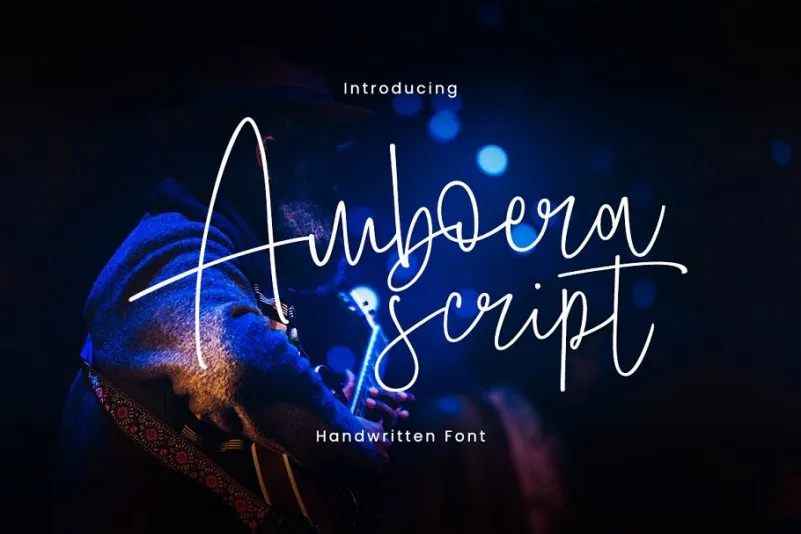
Amboera Handwritten Font – Download Grátis
Descubra a elegância e a naturalidade da Amboera Handwritten Font, uma nova opção para sua paleta de tipos de escrita. Esta tipografia é criada pensando no uso pessoal ou na marca, com um design meticuloso que transmite uma atmosfera amigável e descontraída. Introduzida pela Daikian, a Amboera Handwritten é perfeitamente concebida para ser usada em aplicações formais como cartões de convite, etiquetas, logotipos ou revistas. Ela traz uma verdadeira sensação de personalidade ao seu design, sendo ideal tanto para uso pessoal quanto profissional. O estilo da escrita é neatamente cuidadoso, ainda assim mantendo um certo grau de irregularidade e elegância natural. Isso lhe dá liberdade para experimentar com diferentes aplicações, desde cartões de aniversário até em editoriais de moda ou design gráfico, garantindo que você e seu público alvo encontrem prazer na experiência de usar essa fonte. Seja você um designer de arte digital ou uma marca querendo dar um toque único à sua identidade visual, a Amboera Handwritten é a fonte perfeita para capturar e manter a atenção do seu público. Esta tipografia está aqui para transformar seus projetos em algo ainda mais pessoal e singular.